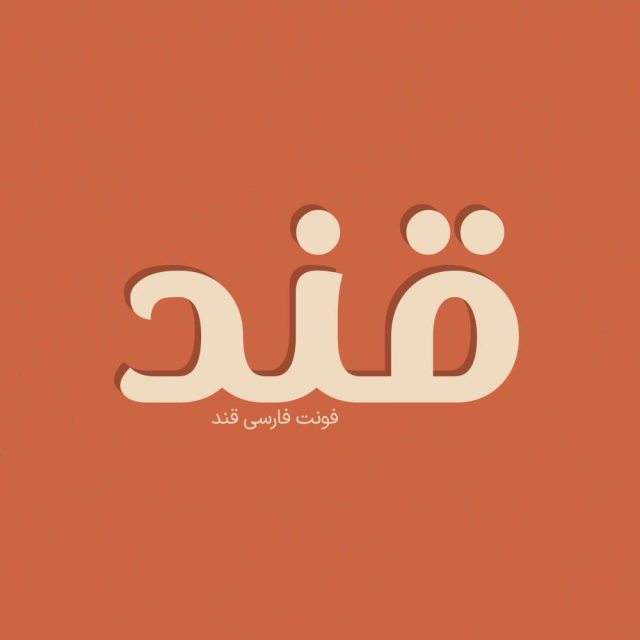
فونت فارسی قند Ghand Font
فونت فارسی قند یک فونت تک وزن با کاربرد طراحی لوگوتایپ و طراحی های مختلف همچون کتاب و تولید محتوای متن های کوتاه و عناوین می…
فونت فارسی قند یک فونت تک وزن با کاربرد طراحی لوگوتایپ و طراحی های مختلف همچون کتاب و تولید محتوای متن های کوتاه و عناوین می باشد. این فونت با ساختار حروف خود مناسب استفاده در لوگوهای نوشتاری می باشد. فونت فارسی قند با تعادل عادلانه ای که بین شکل انسانی حروف و جنبه هندسی آن ترکیب می کند، به ویژگی کاریزماتیک خود دست می یابد. همچنین از این فونت در طراحی تابلوهای چلنیوم هم به دلیل ساختار منحصر به فردش می توانید استفاده کنید. در ادامه برای شما نمونه تایپ های این محصول حرفه ای رو آماده کردیم که میتونید مشاهده کنید.
پیشنمایش و نمونه تایپ های فونت قند